TPフォント使用事例紹介「書籍のタイトル その4」
パッケージや書籍、Webサイト、広告など各媒体でのタイププロジェクトのフォントの使われ方を事例を元にご紹介していきます。
今回は、翻訳書をまとめて紹介します。
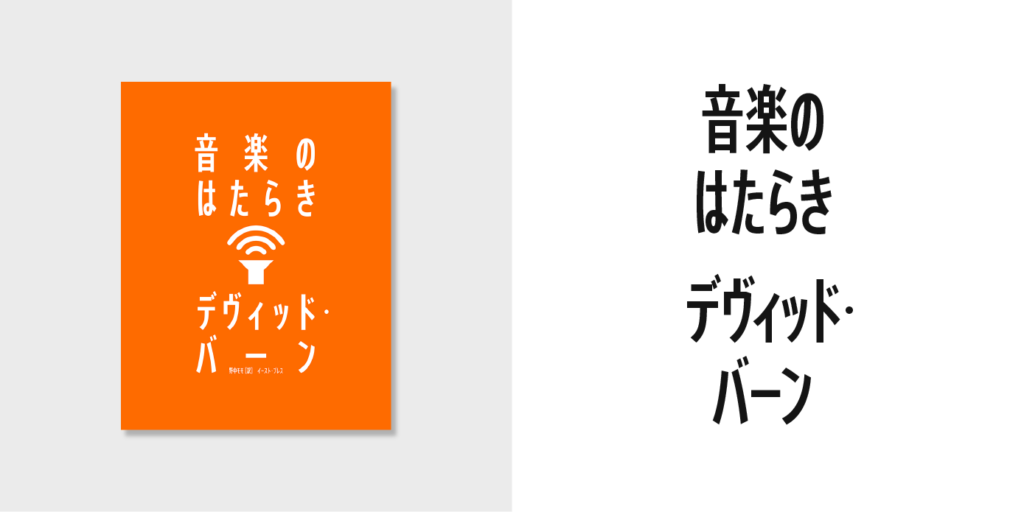
『音楽のはたらき』
著者:デヴィッド・バーン
翻訳:野中モモ
発行:イースト・プレス
【使用されているタイププロジェクトのフォント】
タイトル:AXIS Font コンプレス M
元トーキング・ヘッズのデヴィッド・バーンによる音楽についての書籍のタイトルと著者名にAXIS Font コンプレスが使われています。
目を引くオレンジ色の色面に、白抜き文字とスピーカーのアイコンのみのシンプルなデザインがスタイリッシュでありポップな印象を与えてくれます。
文字間に余裕を持たせた文字組が、シンプルで風通しのよいデザインが特徴のAXIS Fontととてもよく合っています。
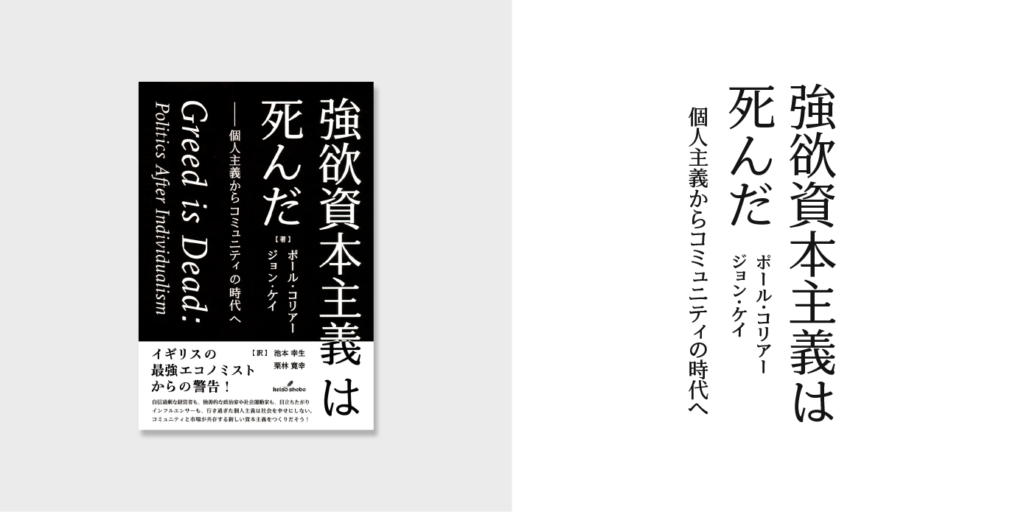
『強欲資本主義は死んだ 個人主義からコミュニティの時代へ』
著者:ポール・コリアー、ジョン・ケイ
翻訳:池本幸生、栗林寛幸
発行:勁草書房
【使用されているタイププロジェクトのフォント】
タイトル:TP明朝 ローコントラスト R
サブタイトル:TP明朝 ローコントラスト M, B
イギリスのエコノミストによる政治、経済についての書籍のタイトルとサブタイトル、著者名にTP明朝 ローコントラストが使われています。
色は白と黒、デザイン要素は文字のみのストイックなデザインがタイトルの内容と相まって緊張感を強く感じさせます。
TP明朝 ローコントラストは、はらいの先端や横画が一般的な明朝体よりも太く作られているため、太いウエイトの明朝体を使うことなく力強さを担保できます。この事例はその好例ではないでしょうか。
ちなみに欧文は、欧文フォントパートナーのGrilli TypeのGT Sectraが使われています。TP明朝との相性もバッチリです!
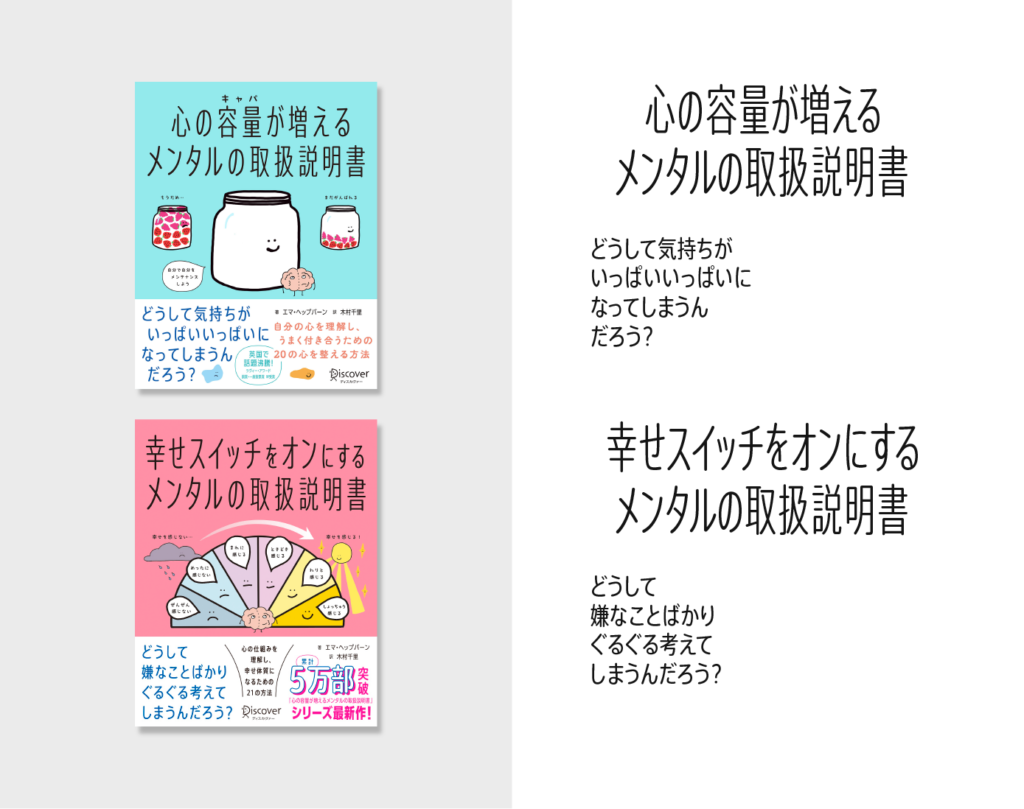
『心の容量が増えるメンタルの取扱説明書』
著者:エマ・ヘップバーン
翻訳:木村千里
発行:ディスカヴァー・トゥエンティワン
『幸せスイッチをオンにするメンタルの取扱説明書』
著者:エマ・ヘップバーン
翻訳:木村千里
発行:ディスカヴァー・トゥエンティワン
【使用されているタイププロジェクトのフォント】
タイトル:AXISラウンド 100 コンプレス L
サブタイトル:AXISラウンド 100 コンデンス R
心理学やメンタルヘルスについての書籍のタイトルとサブタイトルにシリーズを通して、AXISラウンド 100 コンプレスとAXISラウンド 100 コンデンスが使われています。
可愛いイラストと細めの長体丸ゴシックが親しみやすさと共にスッキリとした印象を与えてくれます。
AXIS Fontのシャープな表情は残しつつ、丸ゴシックの長体というユニークな個性を持つAXISラウンド 100のコンデンスとコンプレスがうまく効果を発揮しています。